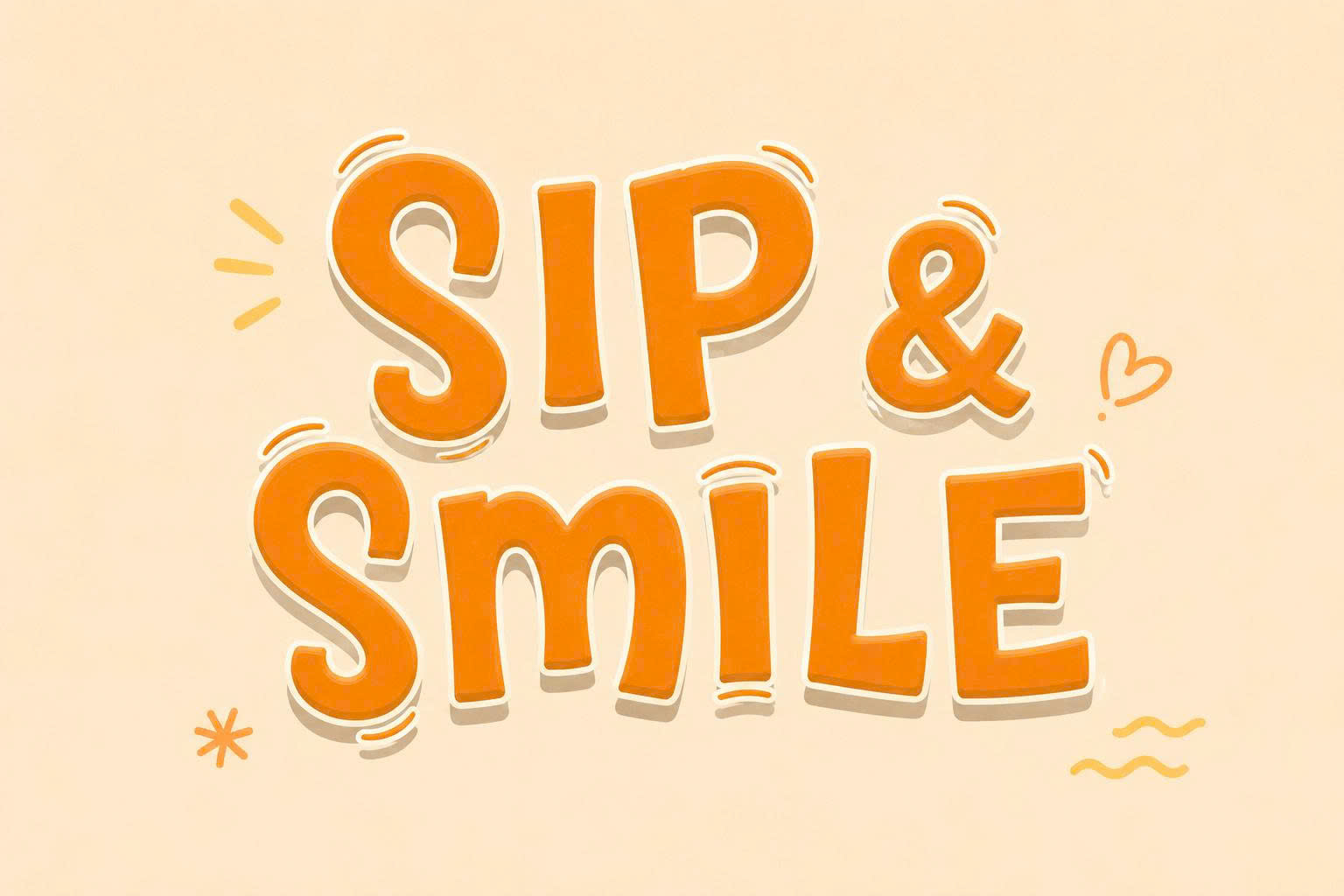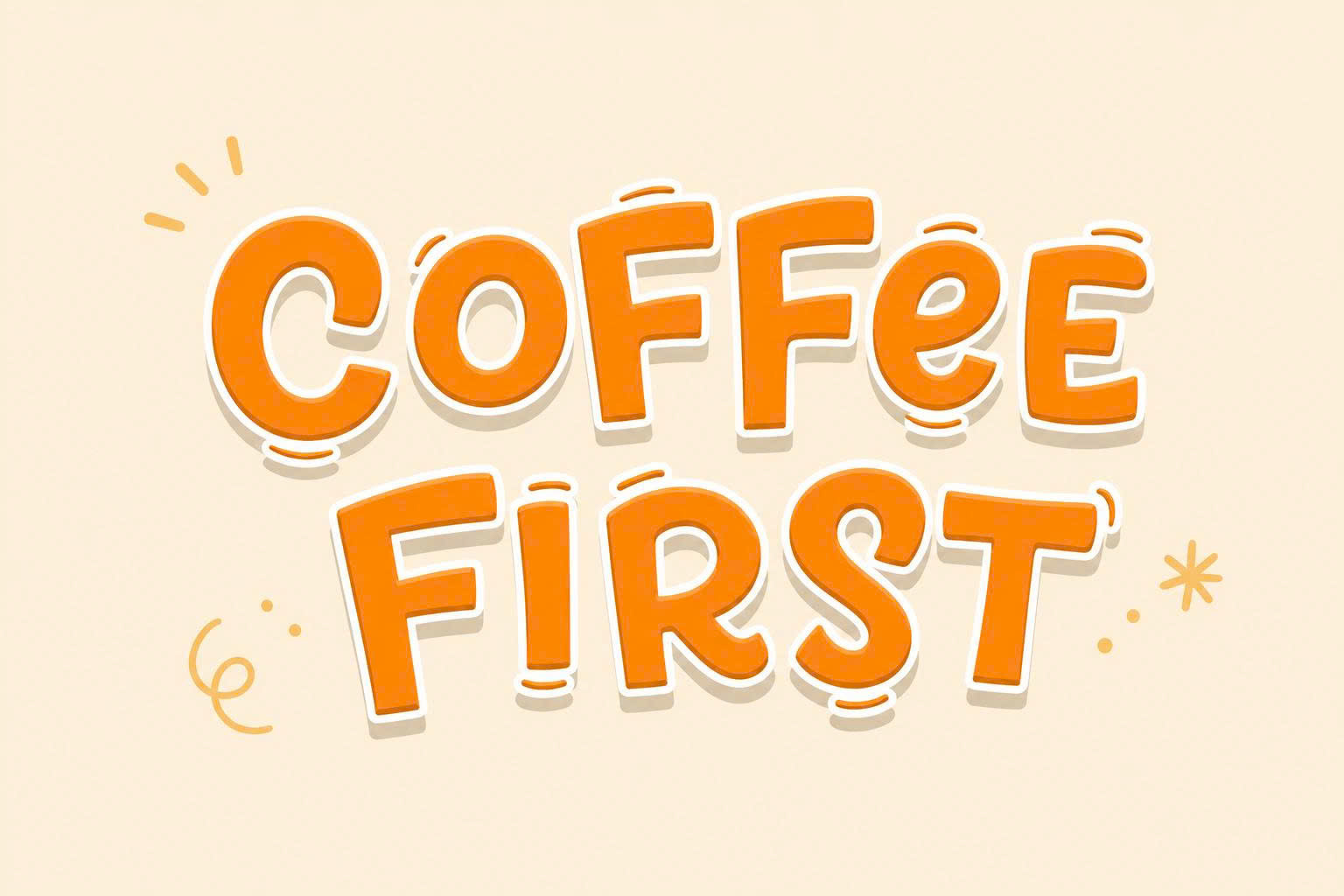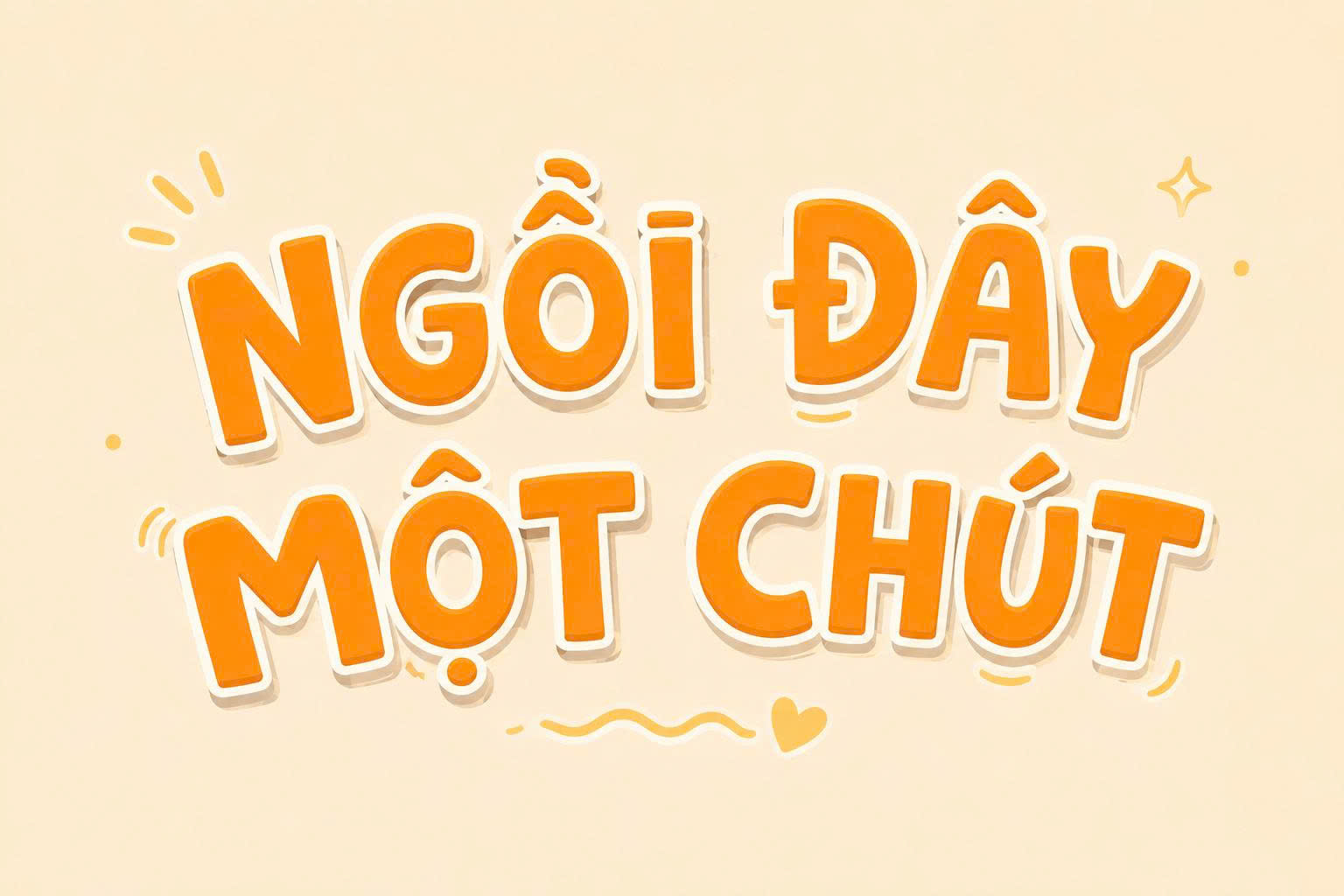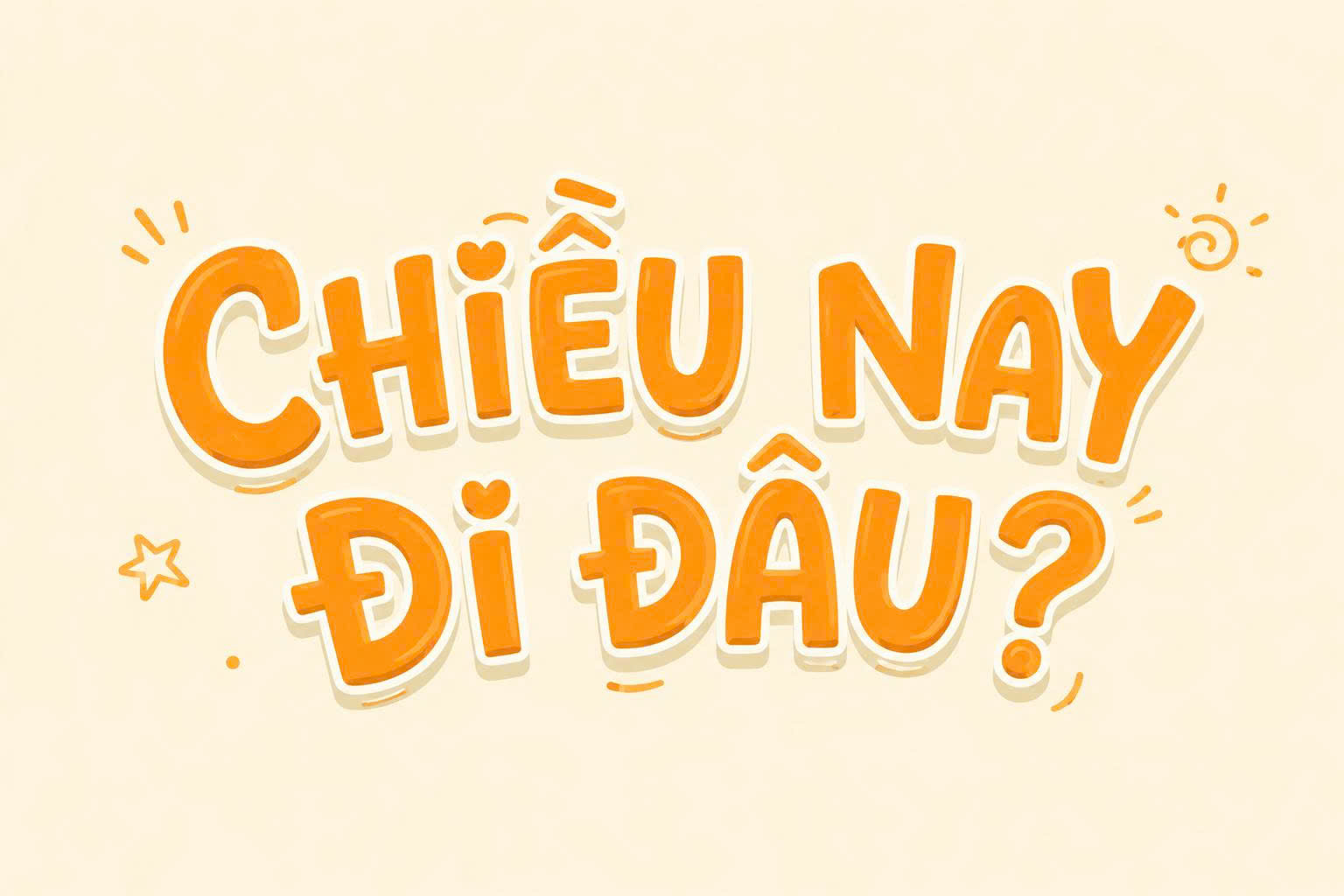
Font Việt hóa MTD Summer Show là bộ phông chữ mang phong cách hoạt hình (Cartoon) đầy vui nhộn, năng động và tràn đầy hơi thở của mùa hè nhiệt đới. Với những đường nét được vẽ tay ngẫu hứng, mập mạp và phá cách, bộ font này là lựa chọn tuyệt vời cho các dự án thiết kế bao bì thực phẩm, poster sự kiện cho trẻ em hoặc các ấn phẩm truyền thông cần sự tươi mới. Doozypack.vn cung cấp link tải font mtd summer show việt hóa chuẩn, giúp bạn sở hữu bộ font mùa hè Việt hóa chỉn chu để sáng tạo mà không lo lỗi hiển thị dấu tiếng Việt.
Đặc điểm nổi bật của font chữ hoạt hình MTD Summer Show Việt hóa
MTD Summer Show không chỉ đơn thuần là một bộ phông chữ, nó mang trong mình tinh thần của sự tự do và niềm vui rực rỡ nắng hè.
Phong cách thiết kế vui nhộn và đầy sức sống
Đặc trưng lớn nhất của bộ font này là các nét chữ có cấu trúc không đồng đều, mô phỏng lại những nhát vẽ tay tự nhiên trên cát hoặc bảng hiệu mùa hè. Các ký tự được thiết kế với độ dày lớn (Bold), tạo nên sự vững chãi nhưng vẫn vô cùng mềm mại nhờ các góc bo tròn. Chính sự phá cách này giúp các dòng tiêu đề trở nên bắt mắt và kích thích thị giác khách hàng hiệu quả.
Hệ thống dấu tiếng Việt được tinh chỉnh nghệ thuật
Nằm trong nhóm summer font Việt hóa chất lượng, phiên bản MTD đã được đội ngũ MTD tinh chỉnh các bộ dấu tiếng Việt sao cho hài hòa nhất với thân chữ gốc. Các dấu thanh (sắc, huyền, hỏi, ngã, nặng) không chỉ đặt đúng vị trí mà còn mang đậm nét hoạt hình, giúp tổng thể bản thiết kế luôn đồng bộ và đạt độ thẩm mỹ cao nhất.
- Phát huy tối đa hiệu ứng màu sắc: Cấu trúc chữ dày cho phép designer thoải mái phối các tông màu rực rỡ hoặc đổ bóng (Shadow) để tạo hiệu ứng 3D cho tiêu đề.